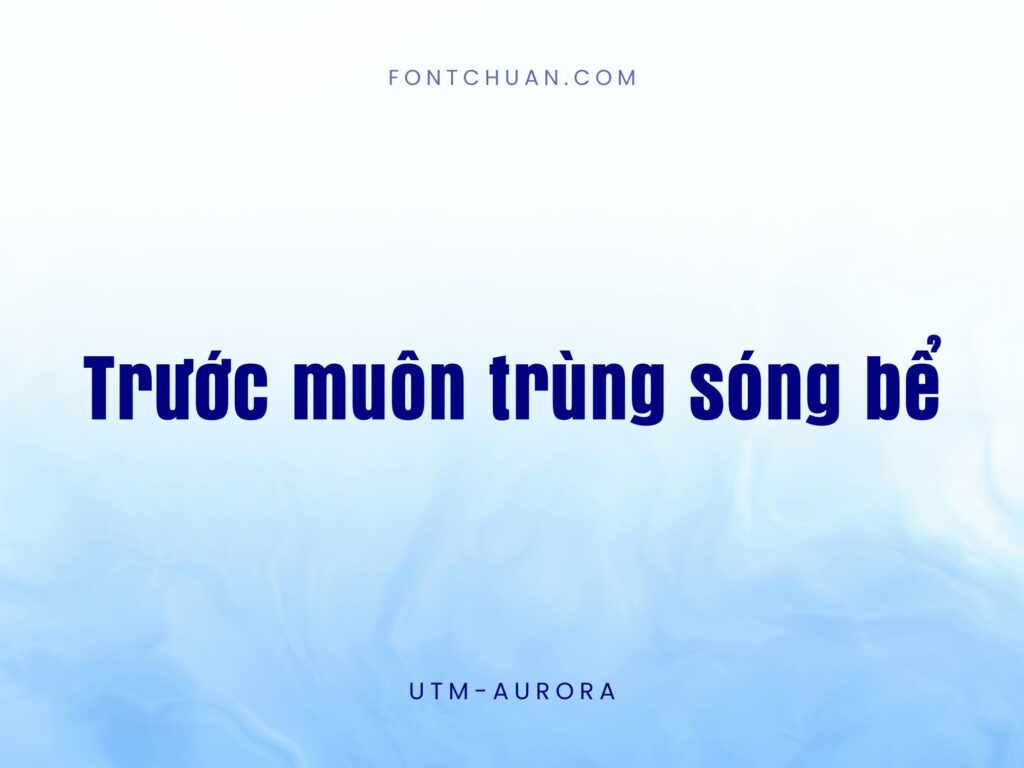
UTM Aurora là phiên bản Việt hóa của kiểu chữ sans-serif hiện đại, mang phong cách tối giản và thanh lịch. Font này được phát triển từ font Aurora gốc, một kiểu chữ mang phong cách Art Deco với các đường nét đặc trưng mạnh mẽ và tinh tế. Phiên bản Việt hóa đã được bổ sung đầy đủ các ký tự có dấu tiếng Việt, làm cho nó trở nên thân thiện và dễ sử dụng hơn với người dùng tại Việt Nam. Đây là một trong những font được thành viên Font Chuẩn sưu tầm và chọn lọc nhằm đáp ứng nhu cầu đa dạng của cộng đồng thiết kế.
UTM Aurora có cấu trúc chữ với các nét đều đặn và hình dáng cân đối, tạo nên sự rõ ràng và dễ đọc. Font này phù hợp cho các ứng dụng như thiết kế logo, tiêu đề, bao bì sản phẩm và các ấn phẩm in ấn yêu cầu sự chuyên nghiệp và hiện đại. Các ngành nghề như quảng cáo, giáo dục, công nghệ và bất động sản có thể tận dụng UTM Aurora để tạo điểm nhấn tinh tế trong thiết kế.